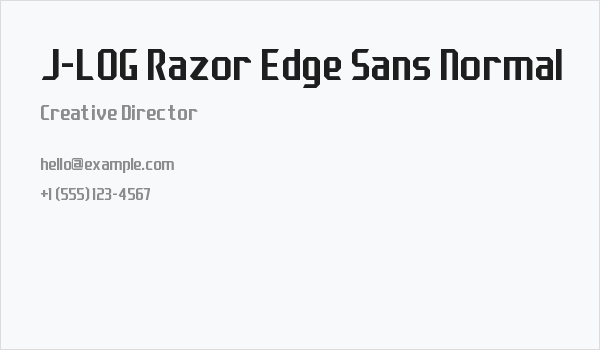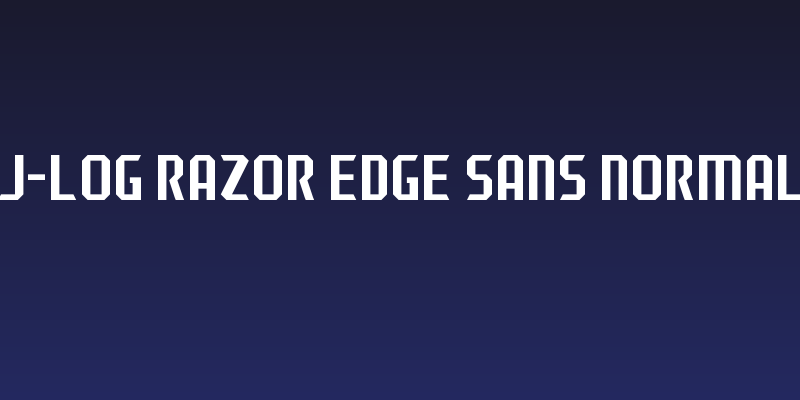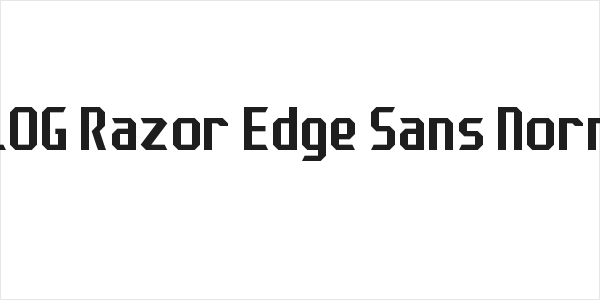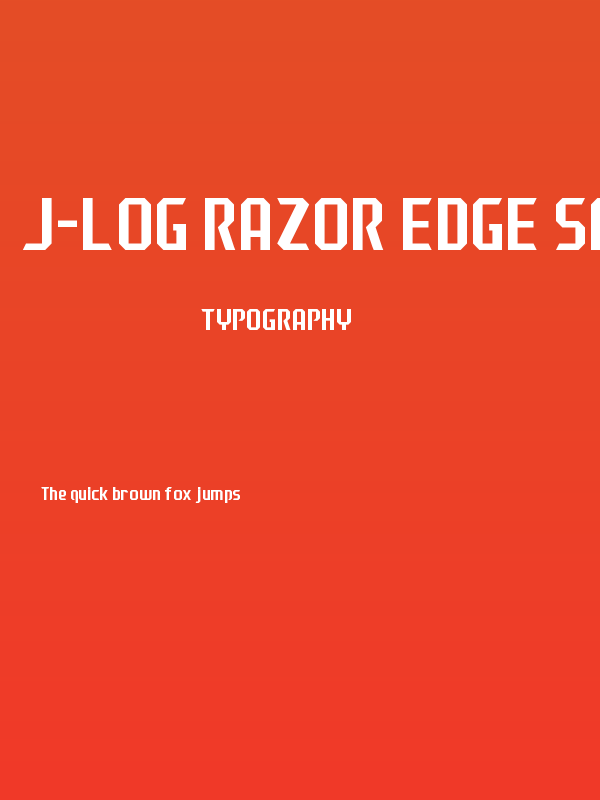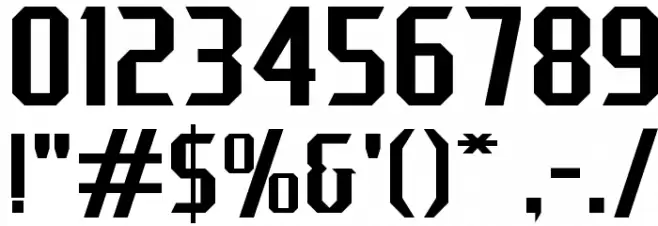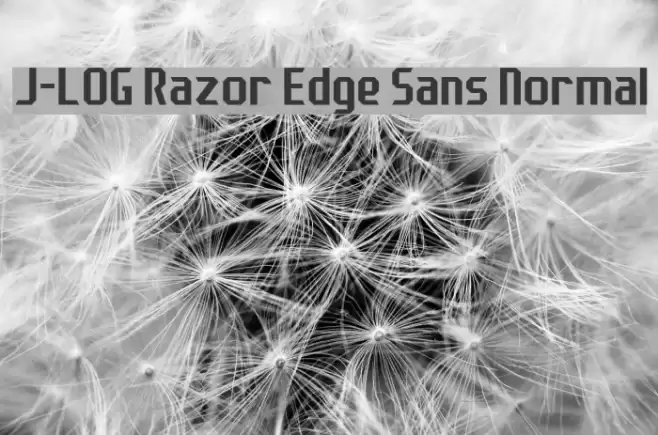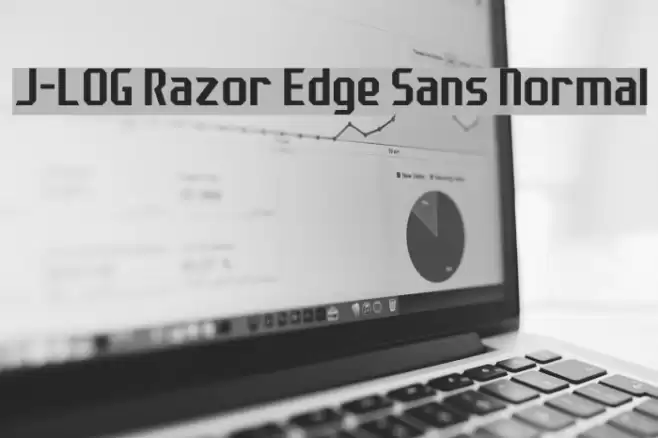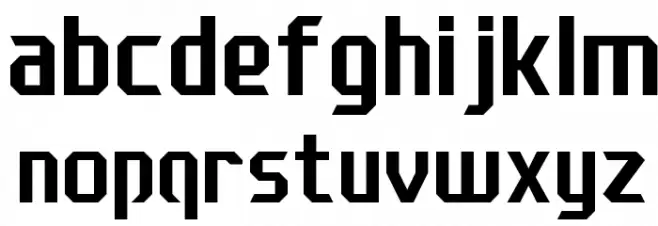
J-LOG Razor Edge Sans Normal Font
| おすすめプロジェクト | Ideal for branding, posters, headlines, and digital interfaces where a modern and edgy look is desired. |